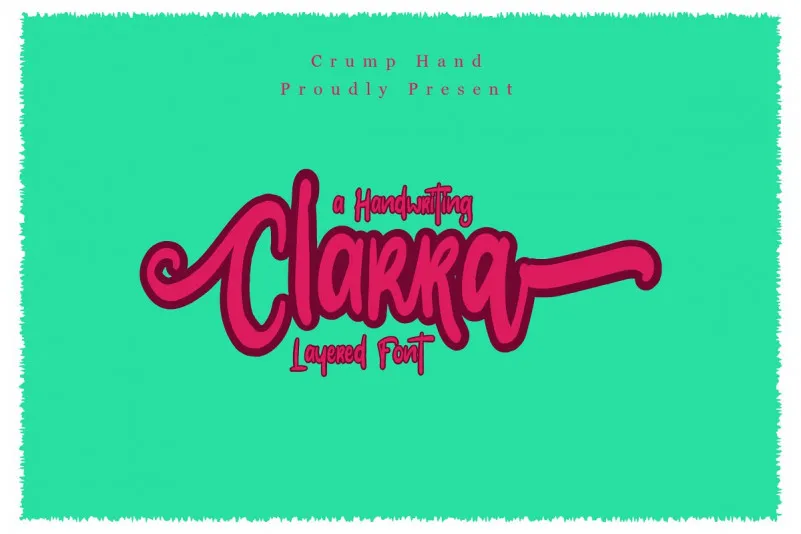
Clarra Layered Script Font – Download Grátis
Esta é uma fonte de destaque que vem com dois camadas em estilo script. Ela representa uma tipografia contemporânea, criada com novos detalhes vigorosos — e variações para uso cromático. Introduzimos a fonte Clarra. É projetada e compartilhada por Crump Hand. Esta fonte é ideal para logotipos, designs de produtos, selos, marcas de água, postagens nas redes sociais, roupas, convites, placas de sinais, clubes esportivos, veículos/motos, eventos especiais ou qualquer coisa que precise da textura de escrever a mão.